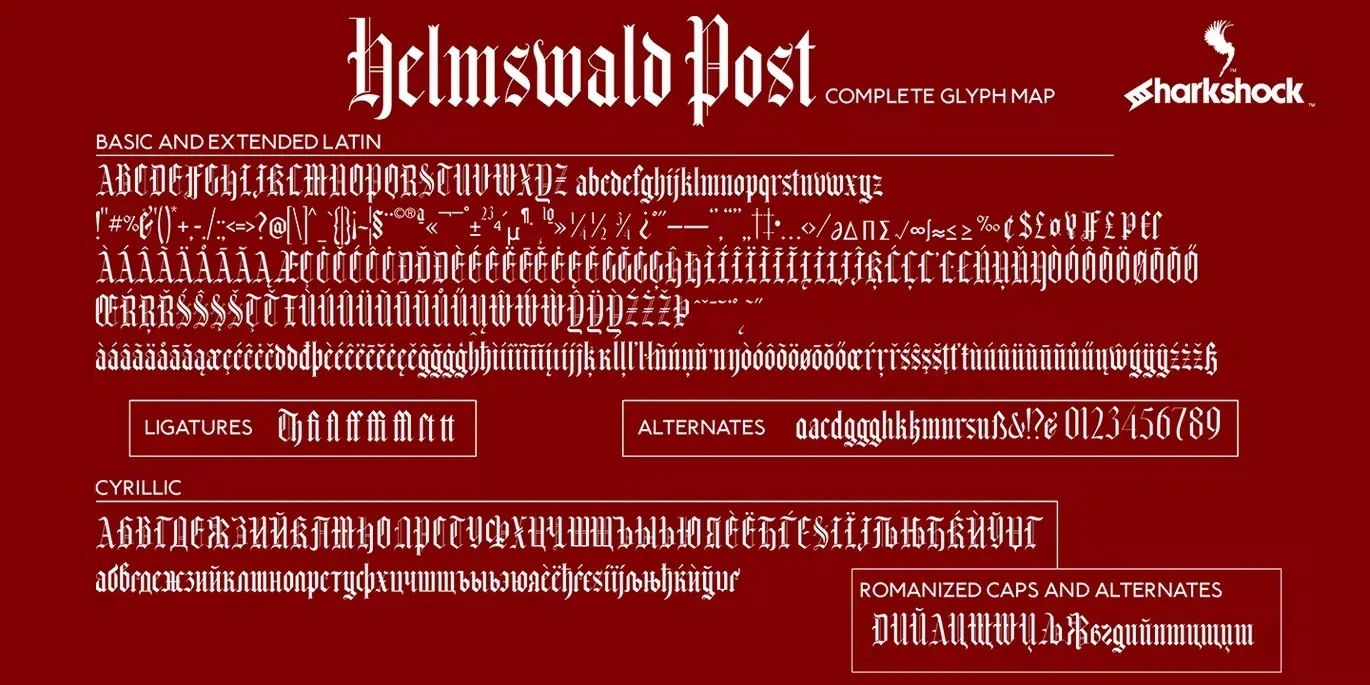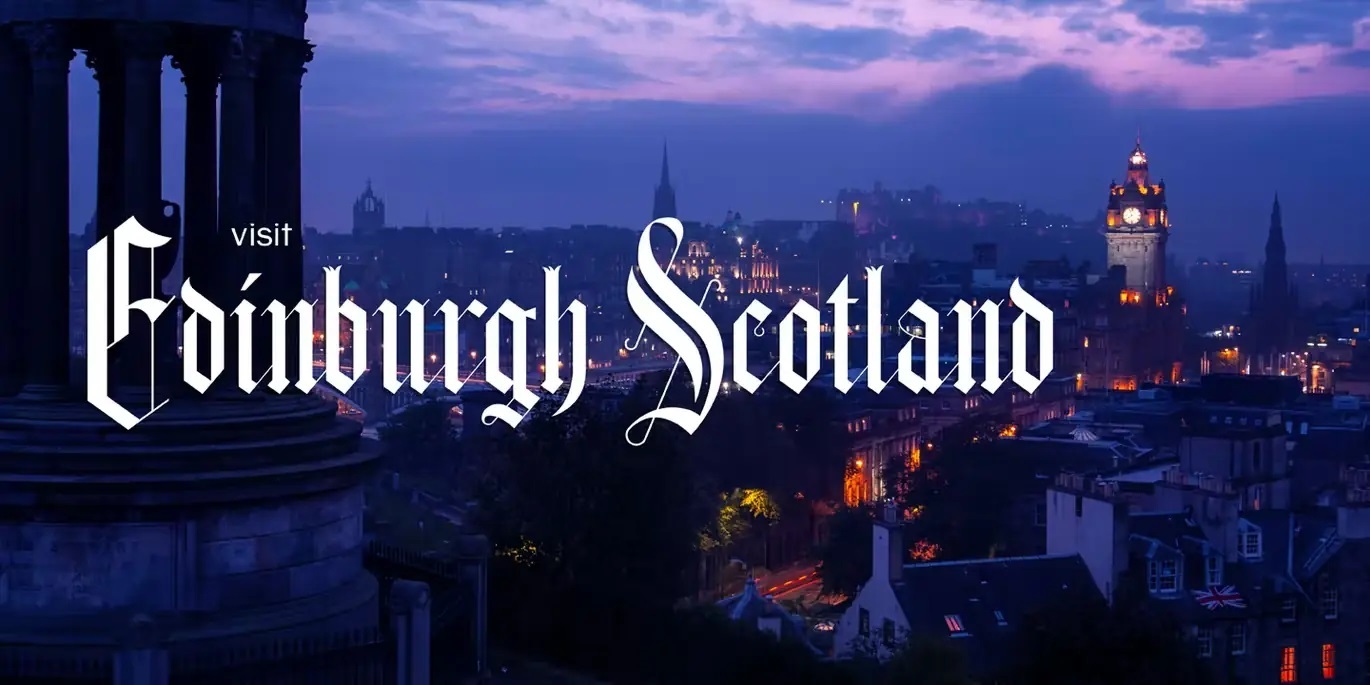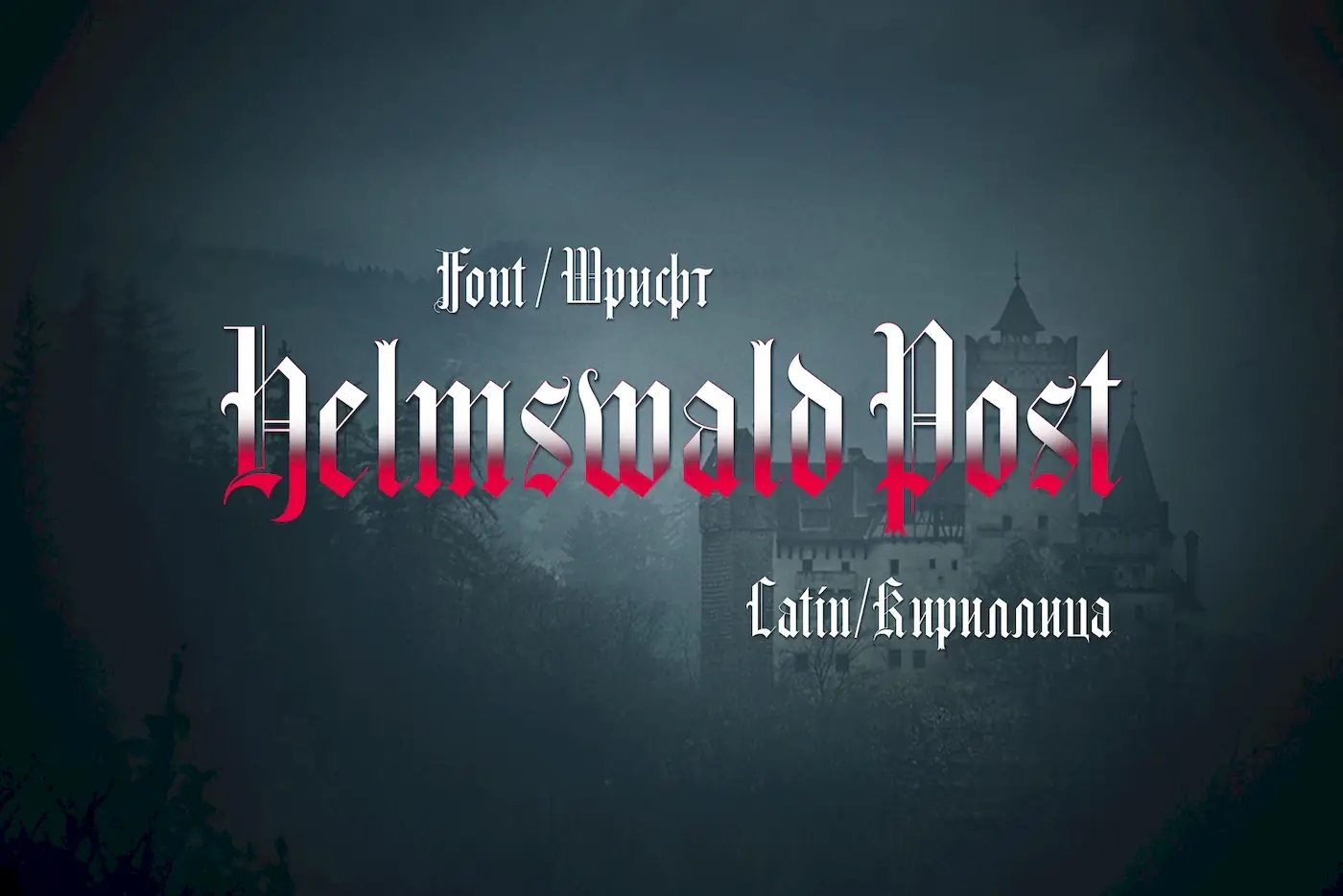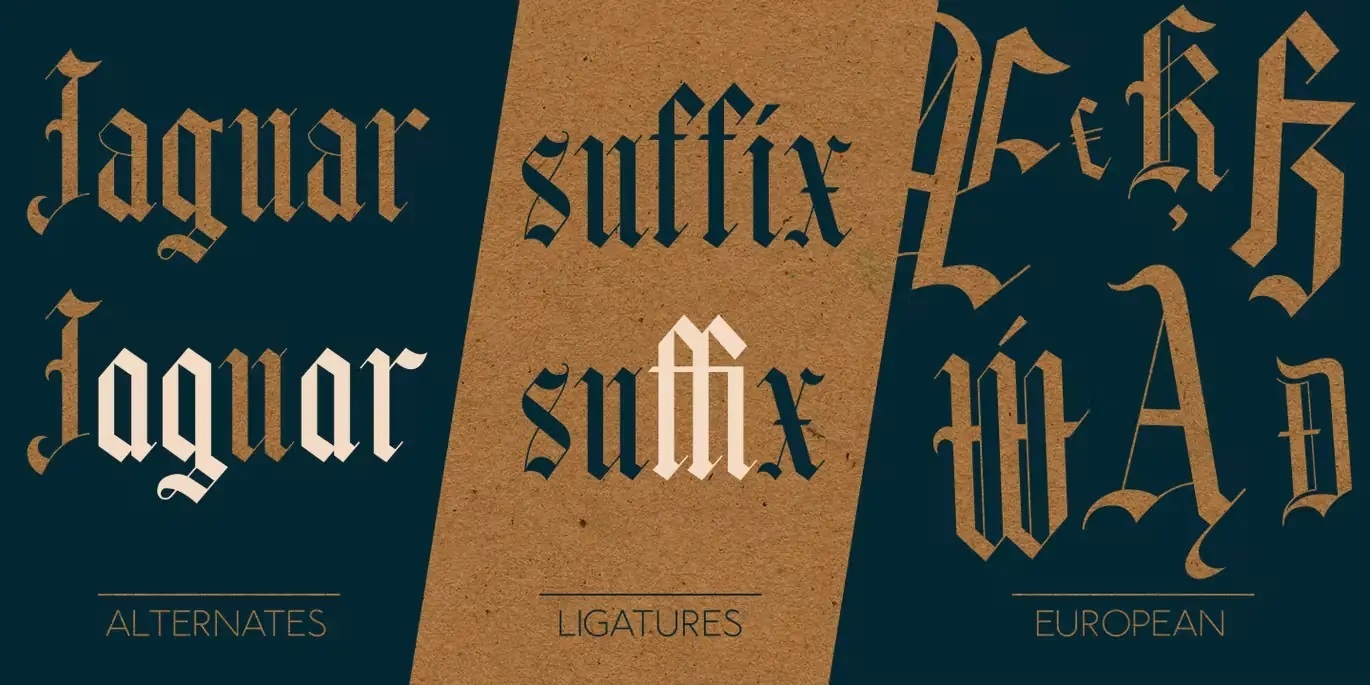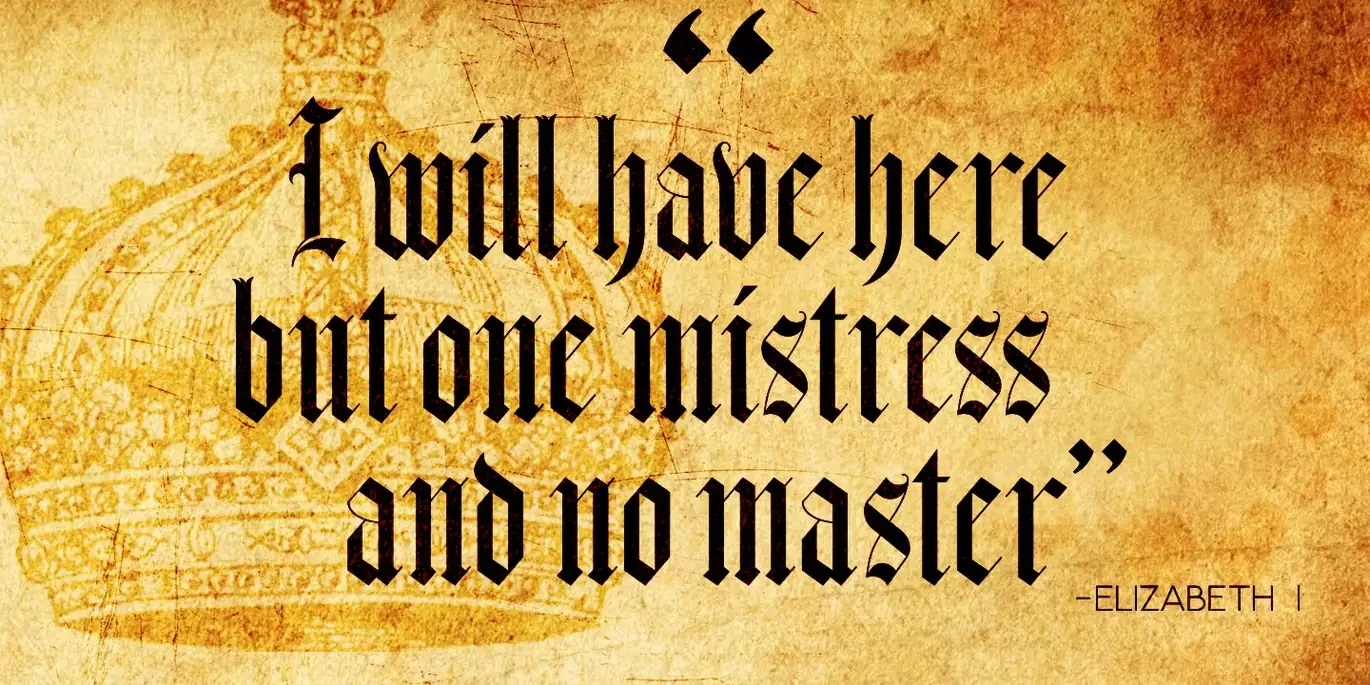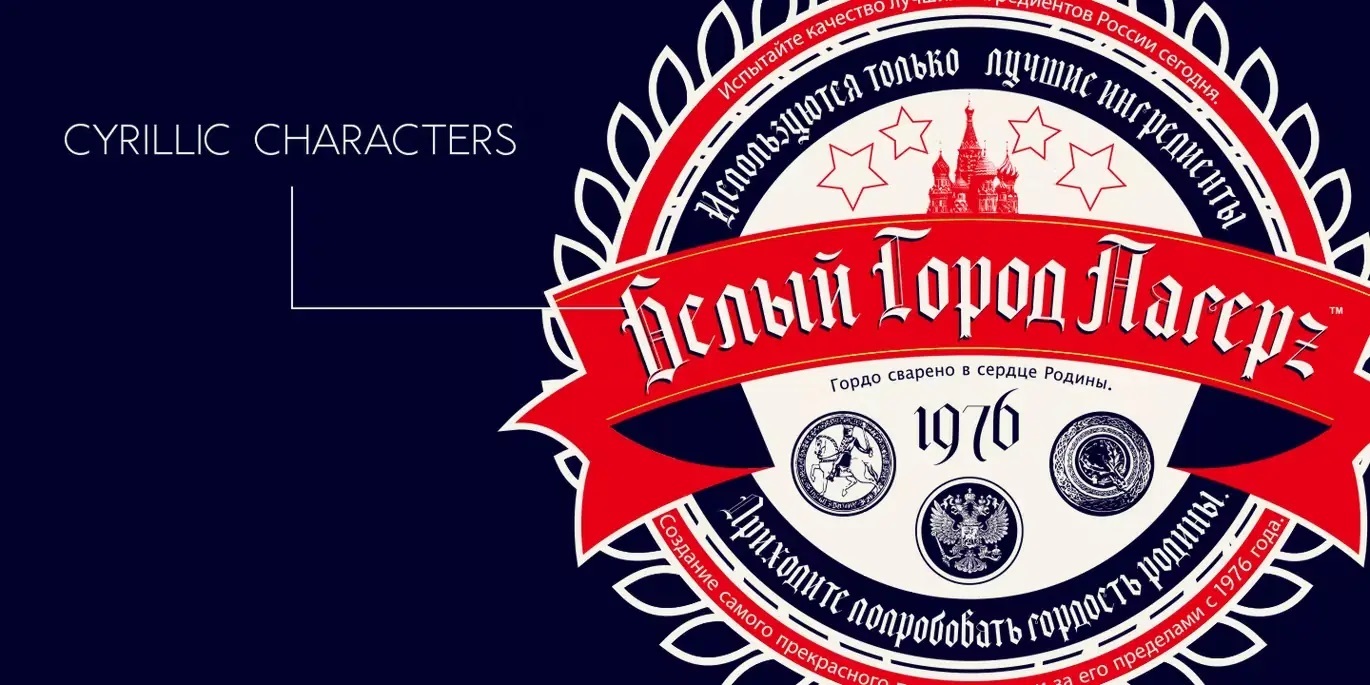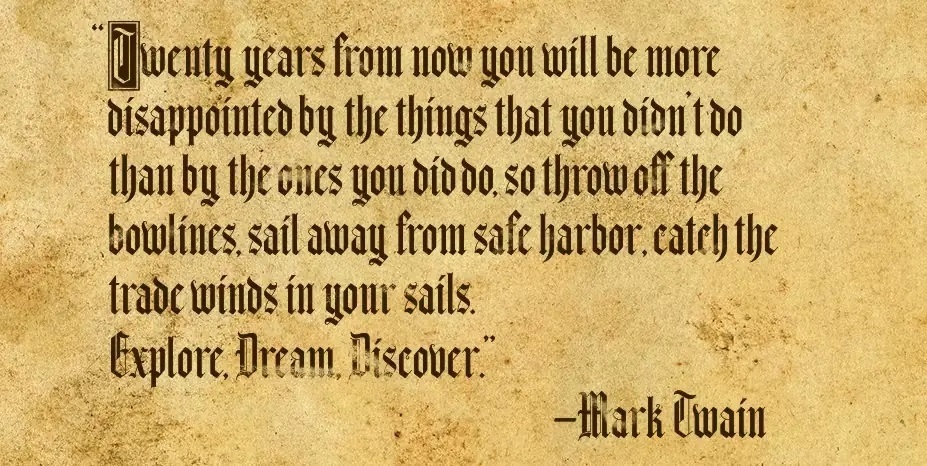
Дополнения Шрифты Татьяна Гапонова 12 сентября 2022 Шрифт Helmswald (Кириллица, Латиница) Красивый шрифт в средневековом стиле для ваших дизайнерских проектов. Формат - OTF, WOFF. Размер - 0.3 мб. Автор: Sharkshock Скачать Шрифт Helmswald (Кириллица, Латиница)